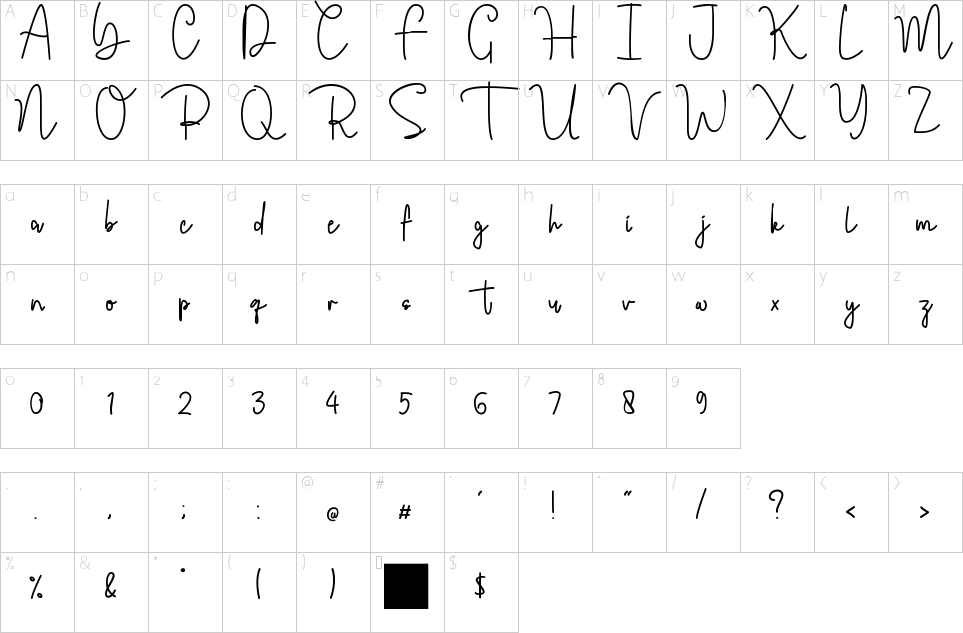
A fonte Jerome Romusha é uma seleção gratuita e moderna para seu próximo projeto de design, especialmente se você está procurando por uma fonte que combine elegância e simplicidade. Desenhada pela incrível equipe de Ffontspedia, Jerome Romusha é uma opção prática e versátil para tanto textos de design gráfico quanto para uso personalizado em suas próprias criações. Com uma elegância clara e uma tipografia minimalista, Jerome Romusha oferece um visual agradável e profissional para qualquer projeto. Essa fonte não apenas se destaca pela sua facilidade de uso, mas também pela grande popularidade, tendo sido baixada mais de 1.745 vezes. Se você está em busca de uma fonte que seja tanto versátil quanto estilosa, Jerome Romusha é um excelente escolha. Ele oferece uma excelente alternativa gratuita para designers de todo o mundo.